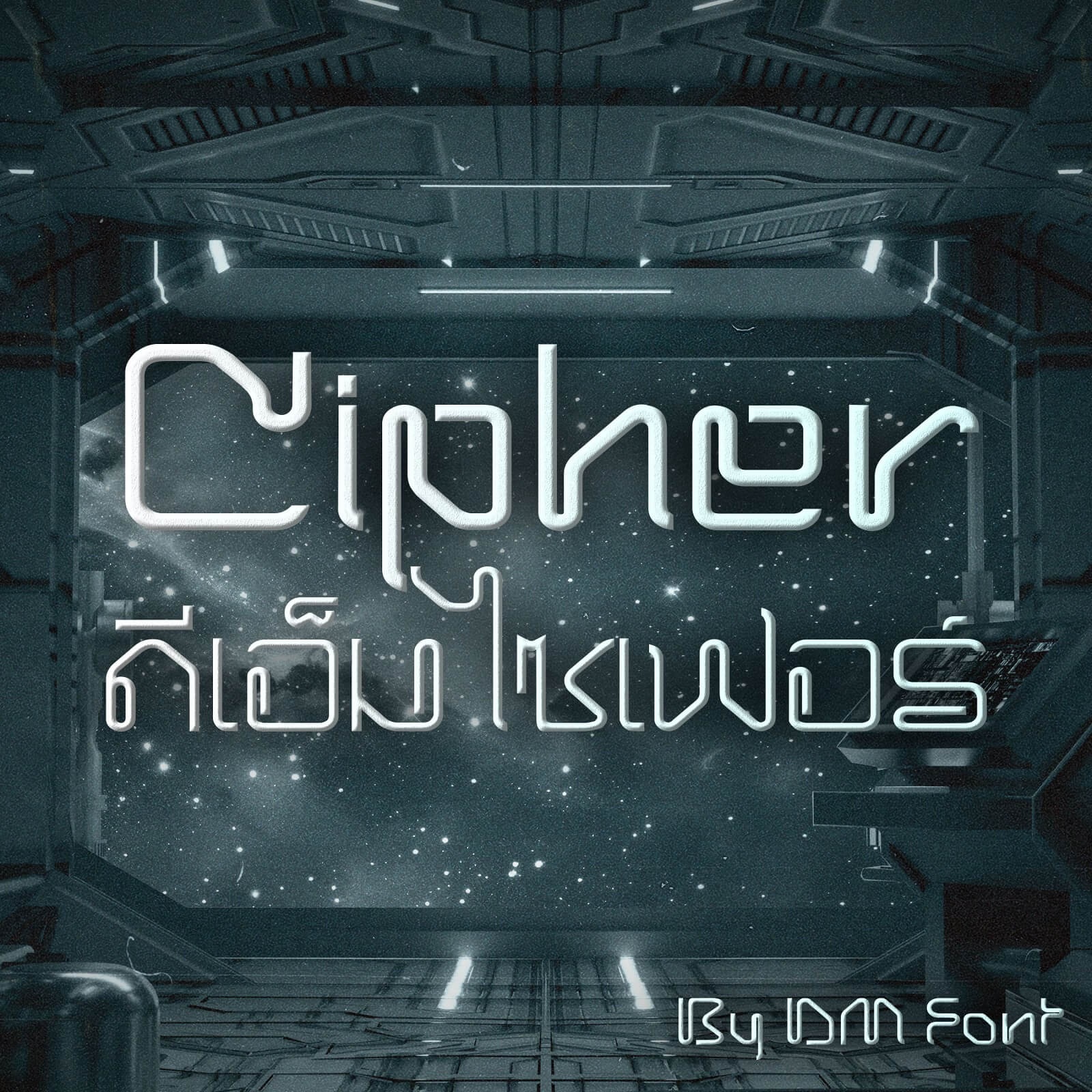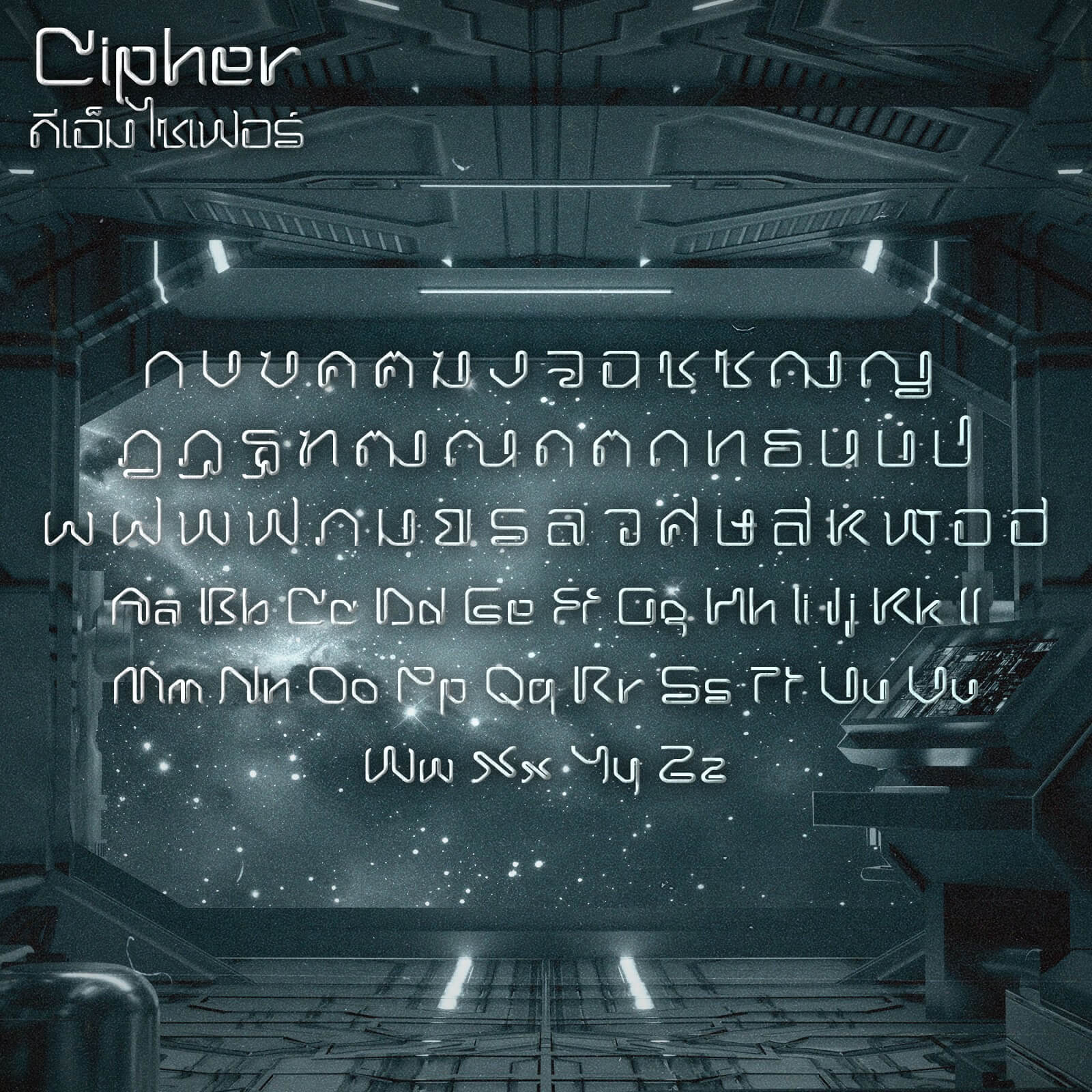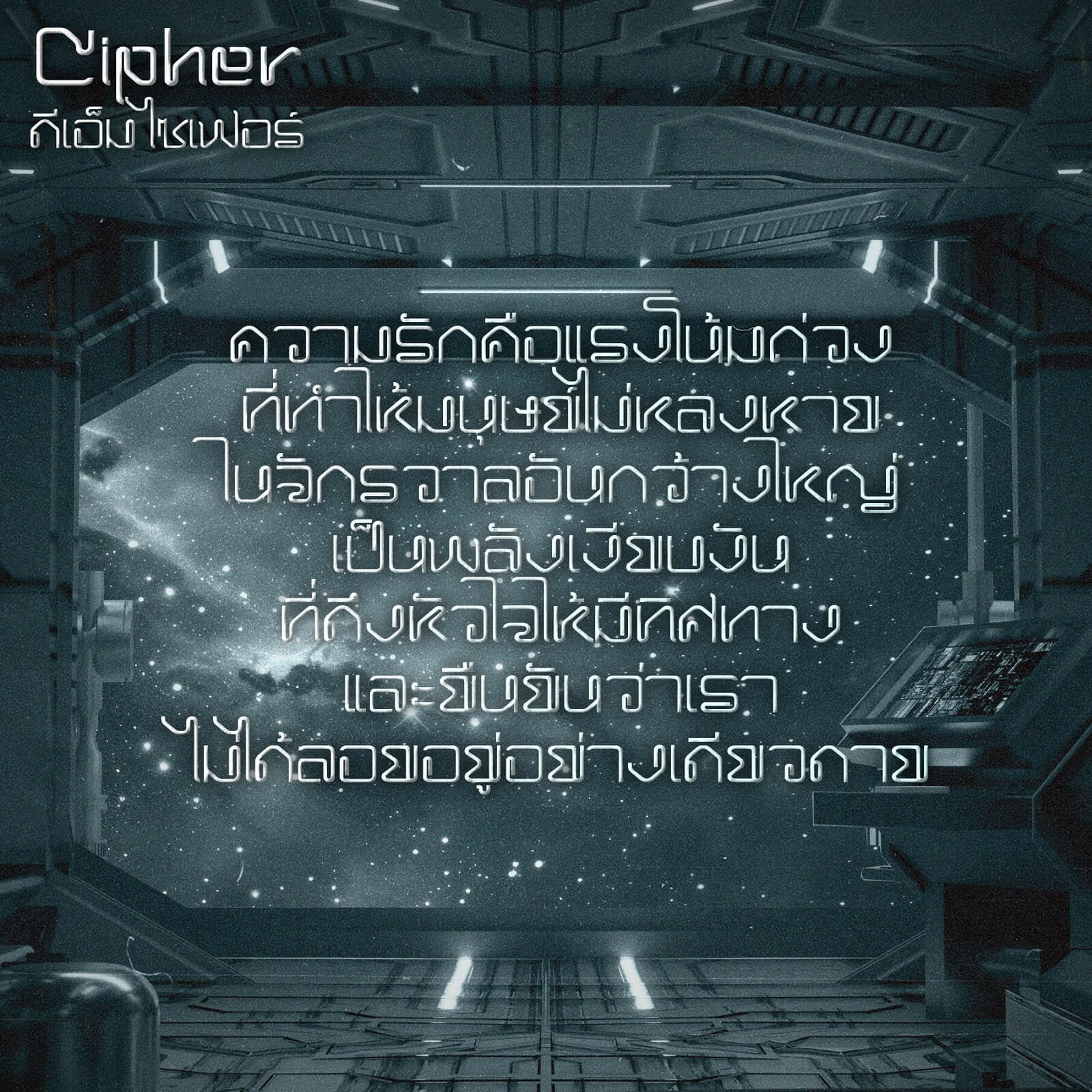
DM Cipher (ดีเอ็ม ไซเฟอร์)
ฟอนต์ที่มีเอกลักษณ์เฉพาะตัว โดดเด่นด้วยเส้นสายโค้งมนและโครงสร้างที่ไม่เหมือนอักษรทั่วไป ให้ความรู้สึกลึกลับ ทันสมัย และเป็นส่วนตัว เหมาะสำหรับงานกราฟิก คอนเซปต์แฟนตาซี ไซไฟ และงานออกแบบที่ต้องการบรรยากาศแตกต่างอย่างชัดเจน